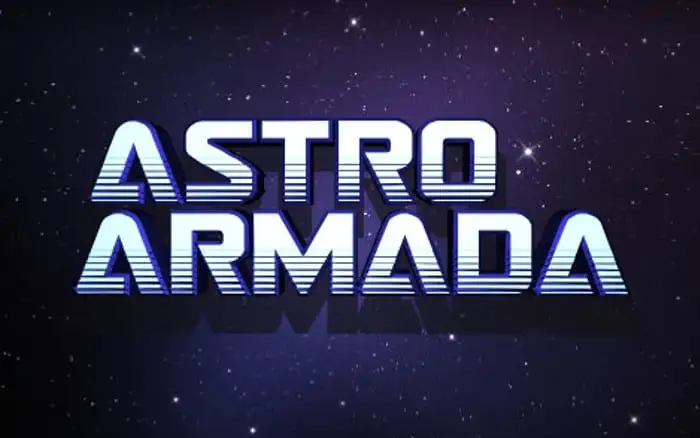
Astro Armada Display Font – Fonte Grátis
Astro Armada Display Font
A Astro Armada Display Font é uma elegante tipografia que combina sofisticação clássica com modernidade natural. Esta família de fontes inclui 28 versões distintas, desde a regular até os tipos semi-itálicos e 3D, garantindo variedade para qualquer projeto. Com suas formas fluidas e linhas leves, essa fonte é perfeita tanto para gráficos elaborados quanto para textos mais limpos e diretos. Combinar o elegante estilo clássico com a frescura da contemporaneidade, Astro Armada Display Font é uma escolha inteligente para qualquer design que busca equilíbrio entre a história e a modernidade. Ideal tanto para marcas como para embalagens de produtos, esta fonte oferece um toque único e sofisticado aos seus projetos.